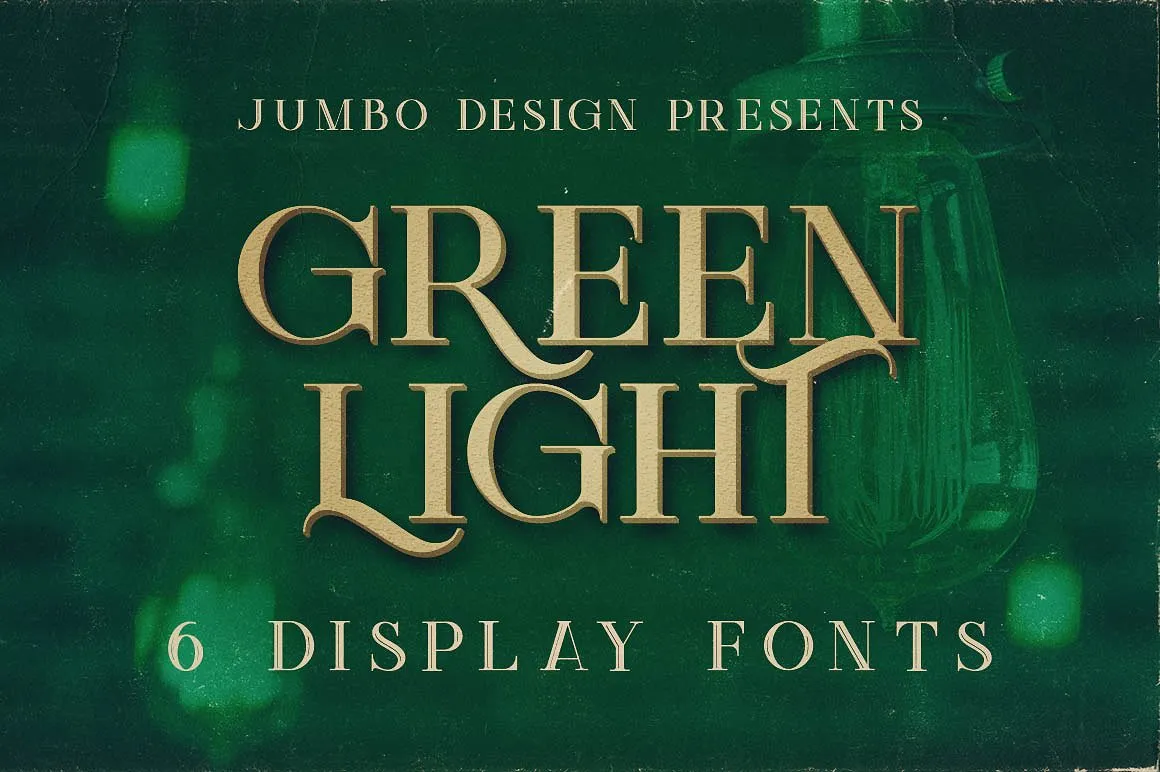
A fonte ‘Green Light Display Font’ é uma escolha ideal para quem procura um estilo vintage retro. Introduzida por JumboDesign, esta font tem um design único e customizado com serifas personalizadas, oferecendo 6 estilos distintos: regular e grunge, bold inline e bold inline grunge, bold e bold grunge. Esta elegante opção de fonte é perfeita para qualquer projeto criativo, desde uma identidade de marca até um design DIY, um título para livro ou até mesmo para letras de casamento vintage, em estilos pop ou retro. É o tipo de recurso que fará sua próxima arte ou projeto gráfica se destacar e parecer moderno e atual. Não importa qual seu propósito, esta font certamente adicionará um toque de elegância e tendência ao seu design.